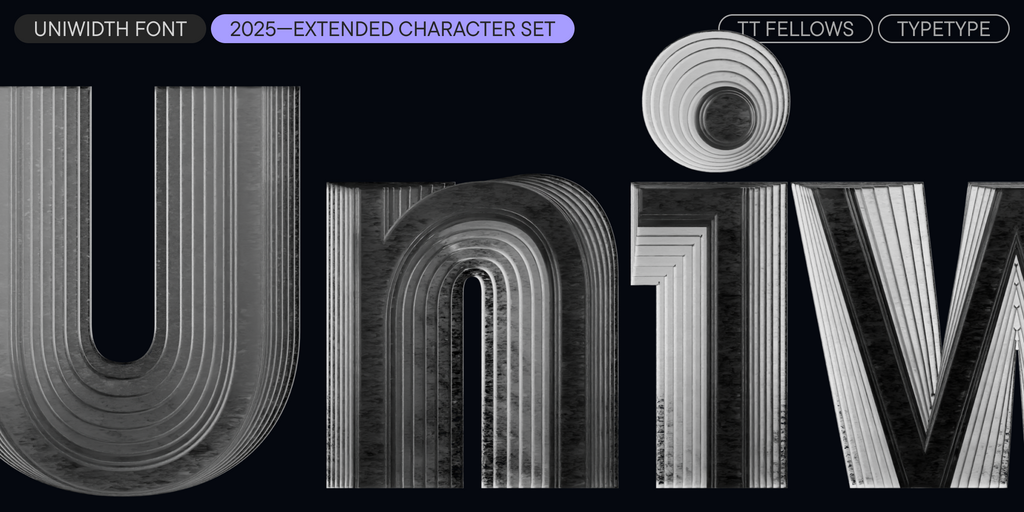
Британские шрифты British
TT Rationalist — функциональный и оригинальный брусковый шрифт с актуальным рисунком. Он универсален и подходит как для заголовков, так и для массивов текста.
TT Fellows — гуманистический гротеск с механистическими мотивами. Открытые формы, дружелюбно-нейтральный характер тонких весов и ещё более мягкий характер в жирных начертаниях.
TT Wellingtons — это гуманистический гротеск, формы которого отсылают к движению ширококонечного пера. Пластичные линии букв обновлённой гарнитуры, присущие английским гуманистическим шрифтам XX века, выглядят актуально и живо в современных дизайнерских проектах.
TT Lakes Neue в версии 2.0 — продолжение геометрического гротеска, вдохновлённого финским функционализмом. Новая версия предоставляет больше возможностей, ведь мы не только увеличили кассовый состав и улучшили шрифт технически, но и доработали его визуальный характер.